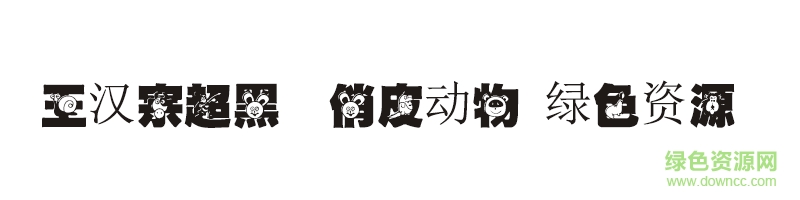
王漢宗超黑體俏皮動(dòng)物字體是一款超具個(gè)性的字體,可以應(yīng)用于海報(bào)設(shè)計(jì)、創(chuàng)意廣告、藝術(shù)設(shè)計(jì)、平面設(shè)計(jì)等應(yīng)用,使用時(shí)請(qǐng)選擇“HanWangyankai”即可,喜歡的朋友快下載收藏吧。
王漢宗超黑體俏皮動(dòng)物是黑體的一種變體,也是藝術(shù)字的一種。特點(diǎn)是筆劃更粗,盡量將空間充滿。同時(shí)為了美觀,對(duì)拐彎處的處理較為圓潤(rùn)。